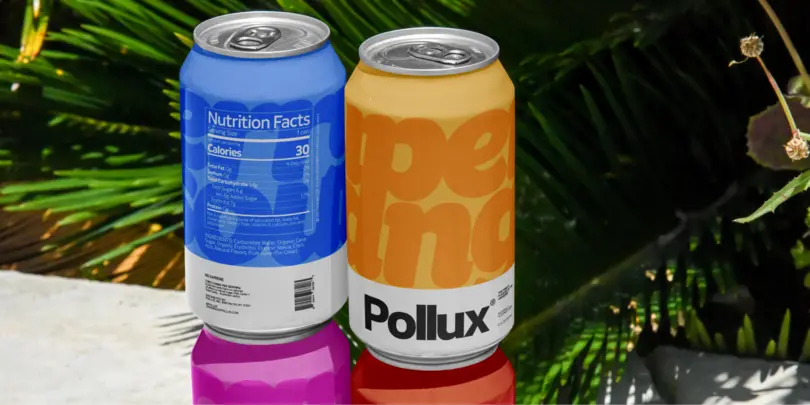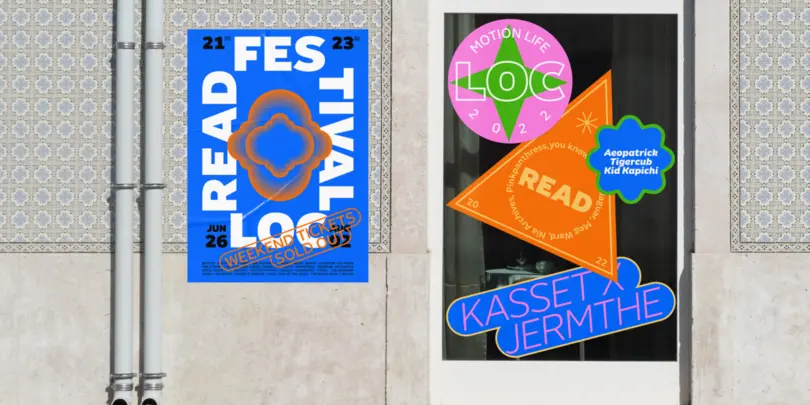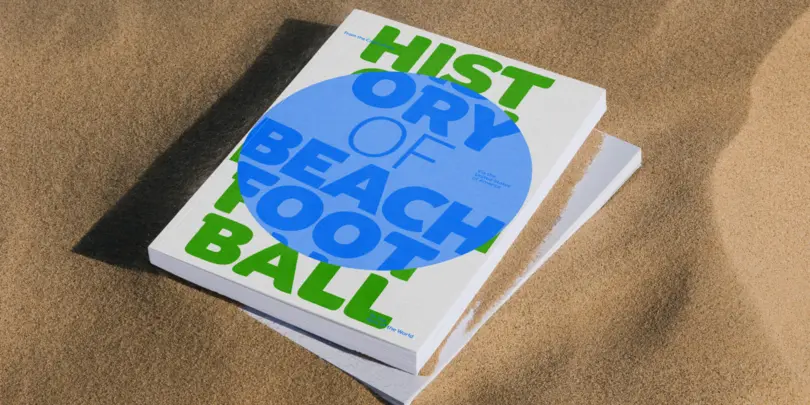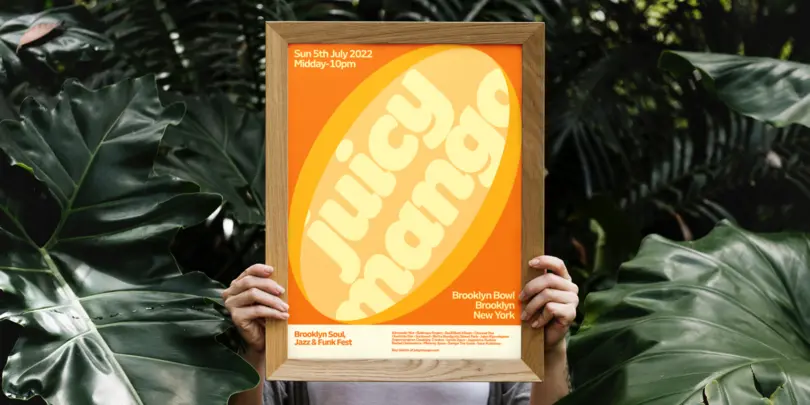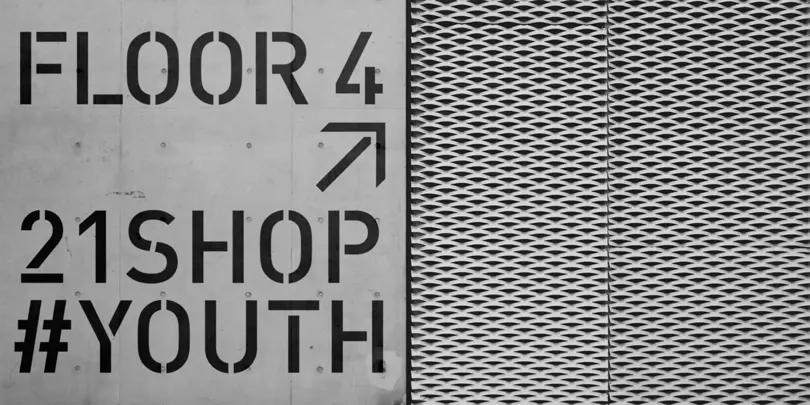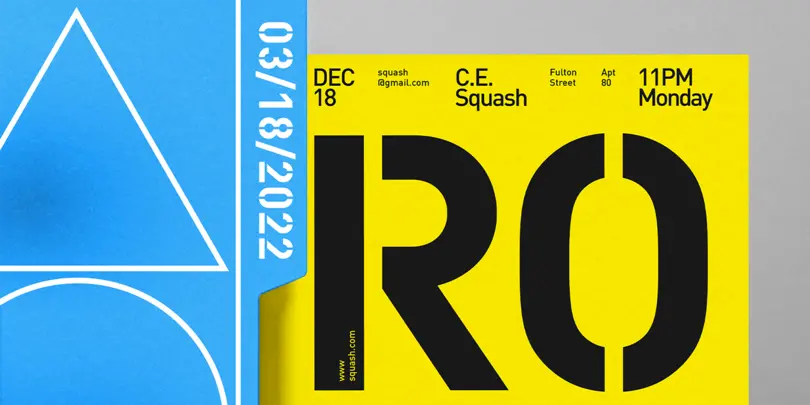
Touvlo
Touvlo est une interprétation dynamique et moderne d’un genre classique, capturant habilement l’esprit des premières polices grotesques britanniques, tout en laissant sa personnalité vive et son énergie briller.
Binate
Binate est une solution intelligente et flexible pour les créatifs modernes. Par essence fonctionnelle, elle offre un mélange synergique de neutralité et d’expression – le tout dans une superfamille contemporaine. Binate vous encourage à expérimenter avec son impressionnante gamme de graisses et vous équipe de nombreux outils pour affiner et modifier à l’infini.
FF DIN Slab
FF DIN Slab arbore avec distinction l’ADN du design d’origine. Elle étend avec dignité la famille DIN – indépendante mais harmonieuse – et apporte des possibilités d’utilisation inédites de toute la famille DIN. Le plus grand soin a été apporté aux serifs de FF DIN Slab : affirmés, robustes et équilibrés. Le résultat de cette attention aux détails est une police qui s’accorde magnifiquement aux autres styles FF DIN.
FF DIN Stencil
Dotée de l’ADN distinctif du design d’origine, FF DIN Stencil offre des possibilités inédites grâce à ses qualités bien à elle et uniques, mais reste fidèle à la philosophie du design FF DIN : la précision de l’ingénierie. La famille FF DIN respire l’esprit de polyvalence et d’assurance, et FF DIN Stencil suit ces mêmes principes avec un petit truc en plus.
FF DIN Variable
Précision, voilà le mantra de FF DIN. FF DIN Variable ne fait pas exception à l’expression de cette philosophie du design. FF DIN Variable vous offre encore plus de FF DIN que jamais. Repoussant les limites de la technologie des polices, les polices variables apportent aux créatifs un outil pour composer des variations particulièrement spécifiques, capables de s’adapter à chaque espace de conception.
Shorai® Sans
Shorai® Sans évoque l’équilibre entre les subtils coups de pinceau traditionnels dessinés à la main et les contours géométriques nets. Basée sur les principes de la conception universelle, avec ses formes de lettres simplifiées et sa vaste gamme de graisses, Shorai® Sans ouvre de nouveaux horizons dans la typographie japonaise.
Tellumo
Pleine de charme, Tellumo est une sans serif humaniste dont la structure géométrique dégage chaleur, élégance et joie de vivre.
Ses capitales alternatives ajoutent une touche d’ampleur et d’éclat aux titres et aux emballages. Son équilibre entre clarté et personnalité la rend parfaite dans le branding et la publicité, dans les designs numériques aussi bien qu’imprimés.
Cotford
Dynamique, adaptable et surprenante – Cotford est une famille de serifs décontractés qui va des graisses thin délicates aux bold audacieuses. Elle s’impose sur chaque page et écran avec une assurance et un charme vintage. Police variable, elle offre aux designers d’infinies nuances et autres secrets bien gardés.